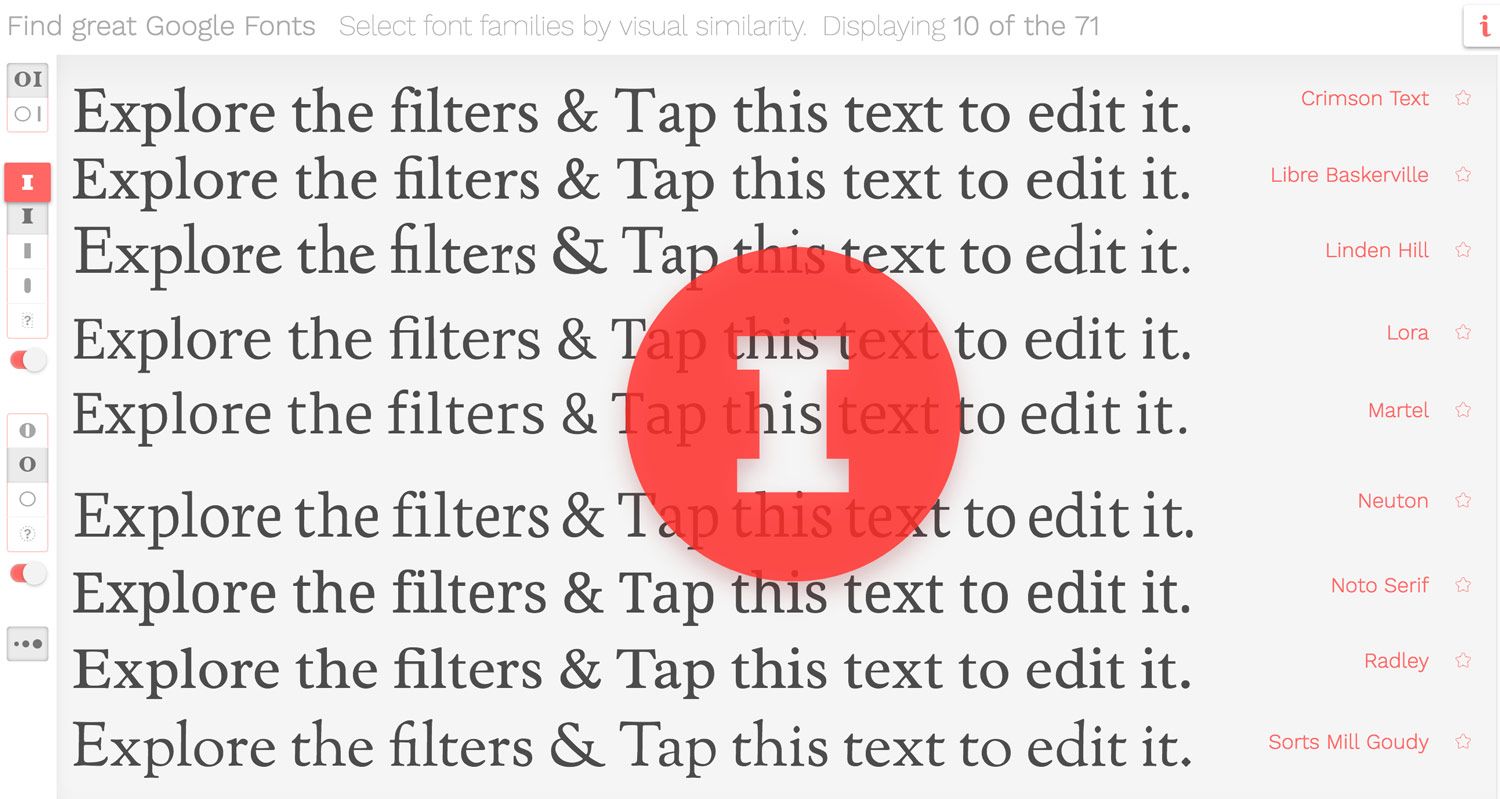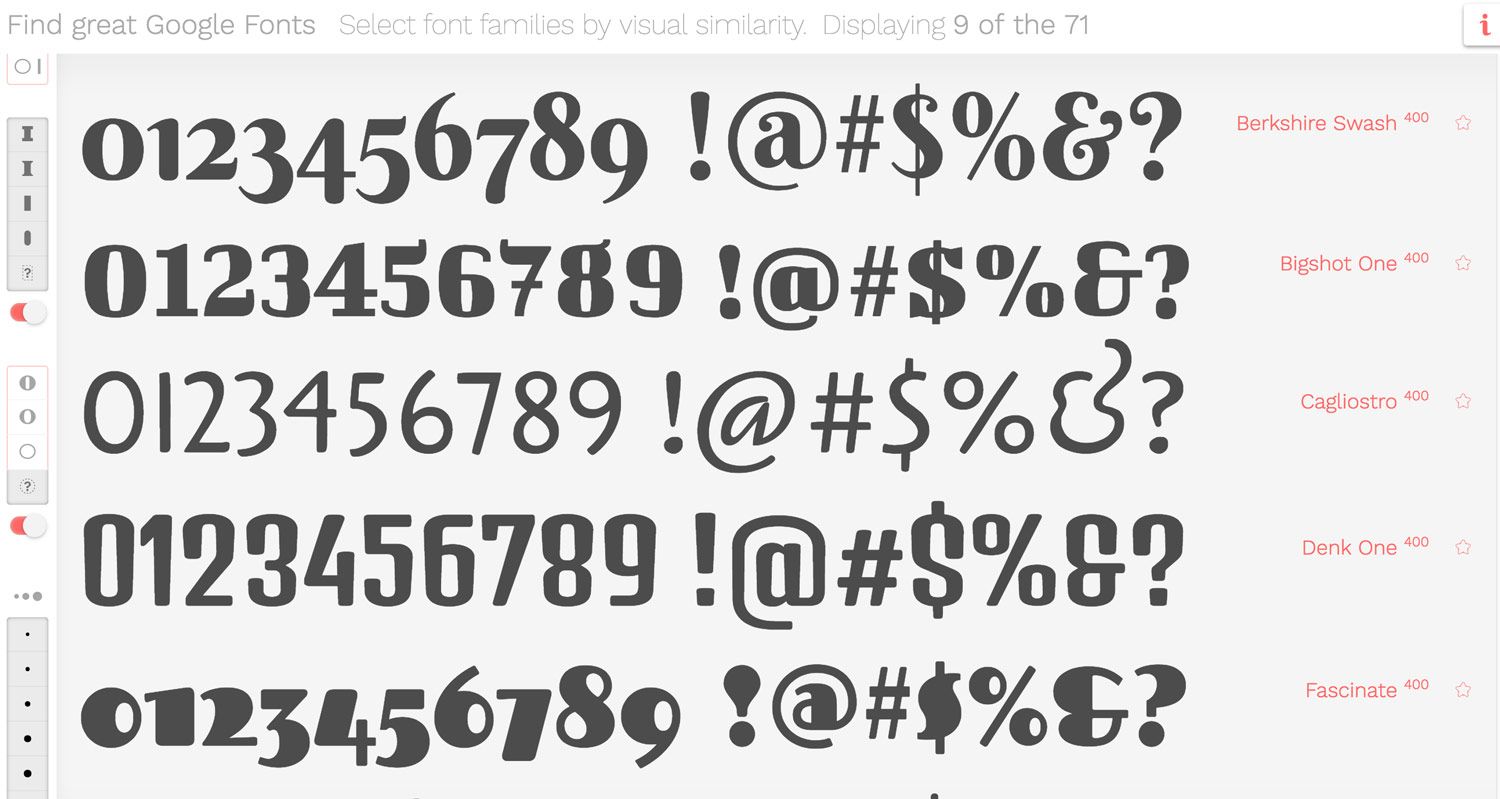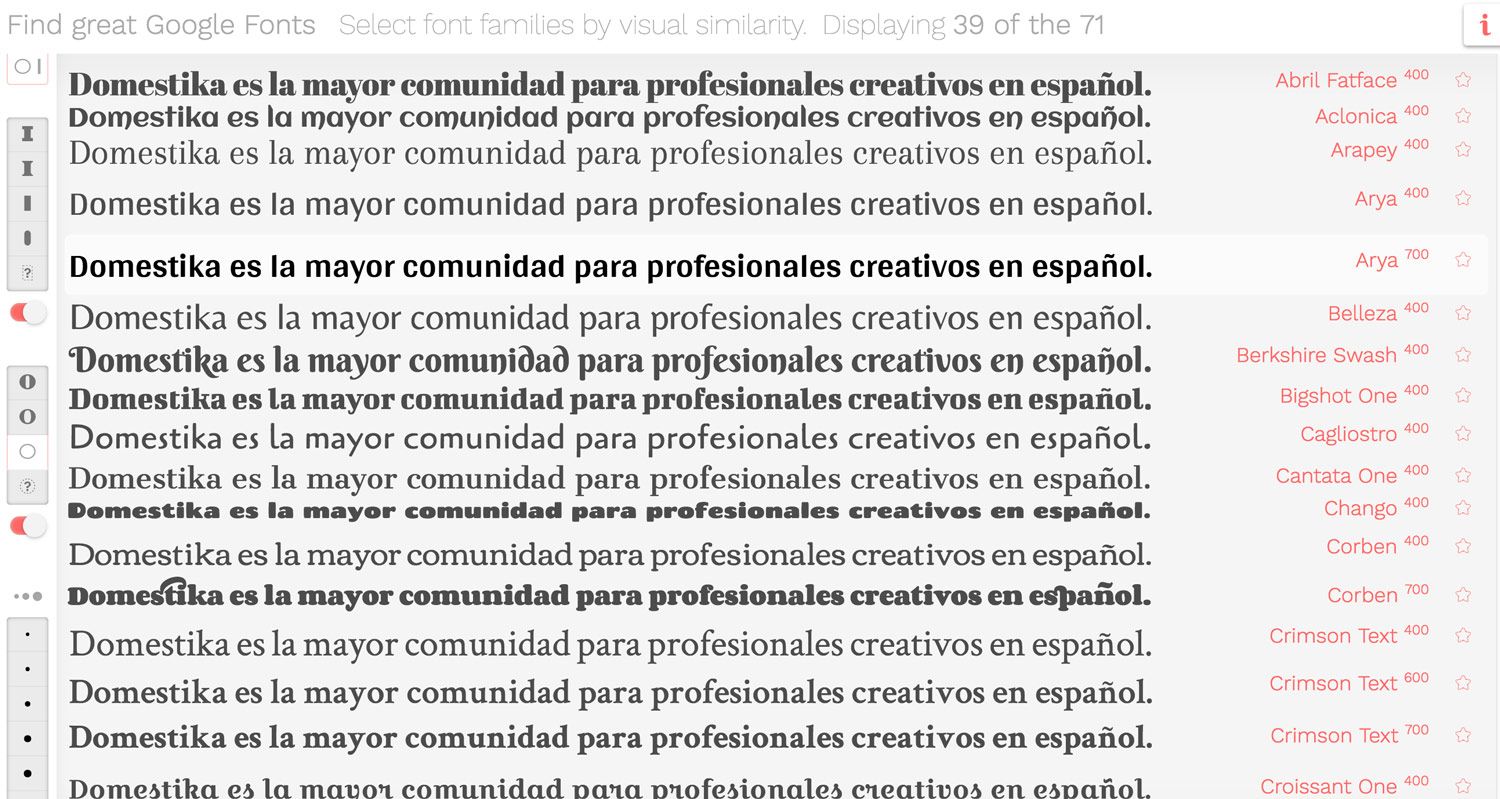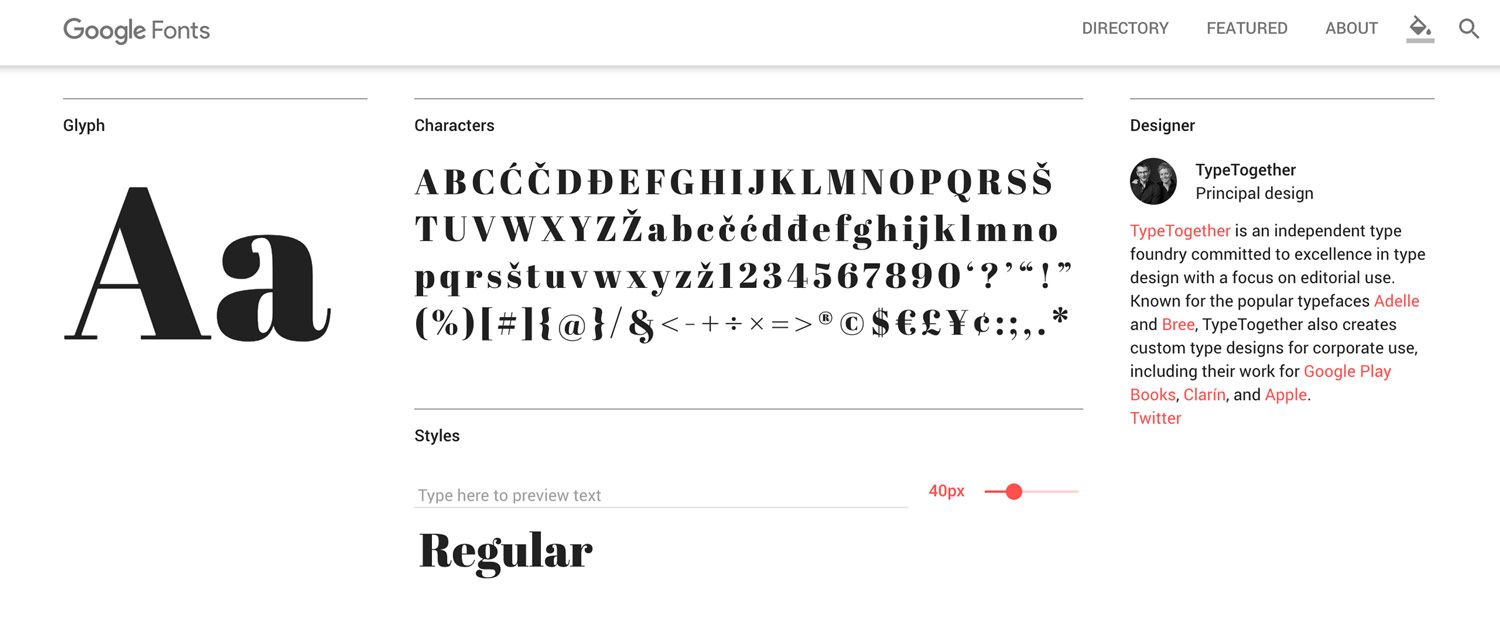
Find great Google fonts, elige la mejor tipografía
Encontrar la tipografía perfecta en la marea de fuentes que ofrece Google Fonts es ahora mucho más fácil.
Google Fonts se ha convertido en la opción favorita de muchos a la hora de elegir una tipografía, especialmente para proyectos web. No es difícil encontrar un tipo de letra adecuado entre las 832 familias que componen su catálogo y se hace especialmente útil cuando nos damos cuenta de que soportan más 135 idiomas. Pero en una colección tan vasta, a veces, la tipografía ideal puede hacerse un poco cuesta arriba.
Find great Google fonts, elige la mejor tipografía 1
Find great Google fonts es una web que ha nacido precisamente para hacer frente a esa necesidad. De una manera completamente visual, ordena las tipografías según su aspecto formal, incidiendo en el tamaño y forma de sus serifas, por ejemplo, y nos permite ver tantos pesos de la misma familia como queramos.
Find great Google fonts, elige la mejor tipografía 3
En un solo vistazo Find great Google fonts nos muestra todas las tipografías gratuitas de Google Fonts que se adaptan a nuestros criterios de búsqueda. Además, la propia web nos permite personalizar el texto que queremos previsualizar, lo que hace todavía más sencillo el proceso de encontrar la tipografía perfecta para nuestro proyecto.
Find great Google fonts, elige la mejor tipografía 5
Find great Google fonts, elige la mejor tipografía 6